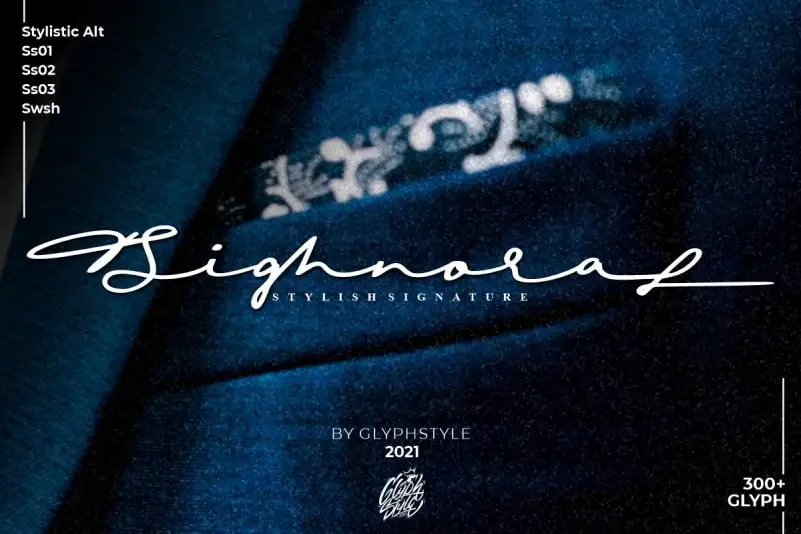
Sighnora Signature Script Font é uma opção irresistível para designers que procuram adicionar um toque sofisticado a seus projetos digitais. Embalada com uma aparência natural e elegante, esta fonte se destaca como uma opção perfeita para estilos de marca criativos, logomarcas de produtos, cartões de empresa, design de casamentos, ou até mesmo para criar um visual único em peças que exigem um toque de luxo. Criada pela equipe do designer GlyphStyle, esta fonte foi projetada para oferecer uma experiência de digitação fluida e fácil de usar, tornando-a uma escolha popular não apenas entre os designers, mas também entre profissionais do design gráfico e criativos. Seja você um especialista em branding ou alguém que simplesmente busca incluir um toque único em suas criações digitais, Sighnora Signature Script Font oferece a perfeita solução de fonte para seus projetos. Sair da descrição original (em inglês): “This signature style font looks natural and is perfect for weddings, watermarks, branding, business, business cards, product logos.” Reescrito em português: Esta fonte de estilo assinatura apresenta uma aparência natural e se destaca perfeitamente para casamentos, marcas d’água, criação de marca, negócios, cartões de empresa e logotipos de produtos.